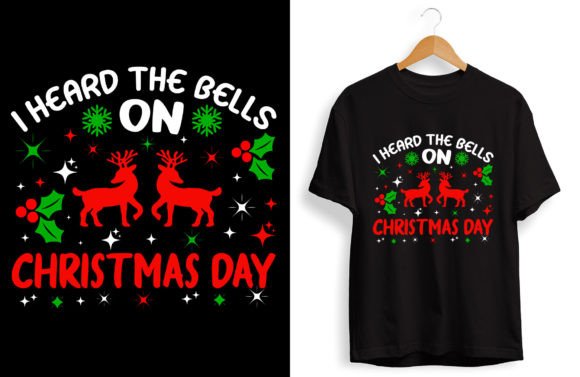
I Heard the Bells on Christmas Day
Trouver les bons éléments de conception peut être un défi, mais I Heard the Bells on Christmas Day propose une collection exceptionnelle qui rehausse instantanément votre travail.
Que vous créiez des produits POD (impression à la demande), des invitations de mariage ou des visuels pour les réseaux sociaux, I Heard the Bells on Christmas Day est un choix idéal.